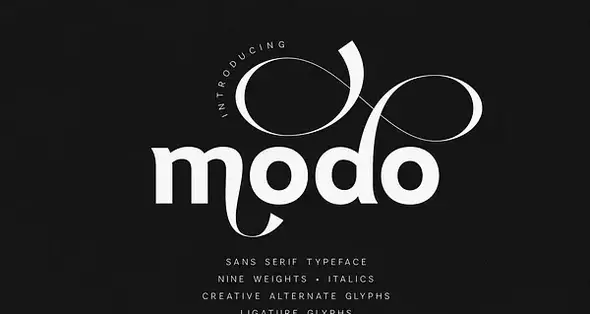
• Modo – Modern Sans Serif Typeface
Modo  فونت سنس سریف مدرن همراه با گلیف‌های جایگزین (Alternates)، لیگچر ها (Ligatures) و پشتیبانی چند زبانه. Modo یک فونت سنس سریف (sans serif) امروزی است که برای ایجاد تعادل میان مینیمالیسم تمیز و ذوق خلاقانه بیانی طراحی شده است. Modo با داشتن 9 وزن (weight) به همراه ایتالیک‌های متناظر، به‌طور یکپارچه از خطوط نازک ظریف تا عبارات بولد (bold) قدرتمند سازگار می‌شود. گلیف‌های جایگزین خلاقانه و لیگچر های شیک آن به (فونت) شخصیت می‌بخشند و آن را برای برندسازی، چیدمان‌های سرمقاله (editorial)، بسته‌بندی، لوگو و تجربیات دیجیتال عالی می‌سازند.
Modo با پشتیبانی از بیش از 85 زبان، کاربرد جهانی را تضمین می‌کند و الفبای گسترده لاتین و نمادهای تایپوگرافی ضروری را پوشش می‌دهد. چه در حال ساختن سرفصل‌های (headlines) پیچیده، متن بدنه (body text) مینیمالیستی، یا نمایشگرهای چشم‌نواز باشید، Modo یک راه‌حل تایپوگرافی همه‌کاره برای طراحان مدرن ارائه می‌دهد.
ویژگی‌های کلیدی:
• فونت سنس سریف با طراحی مدرن و همه‌کاره
• 9 وزن + ایتالیک‌های متناظر (از Thin تا Black)
• گلیف‌های جایگزین خلاقانه و گزینه‌های لیگچر
• پشتیبانی گسترده زبانی (بیش از 85 زبان)
• عالی برای برندسازی، بسته‌بندی، مجلات، پوسترها، منوها و طراحی دیجیتال
Modo – Modern Sans Serif Typeface with Alternates, Ligatures & Multilingual Support
Modo is a contemporary sans serif typeface designed to balance clean minimalism with expressive creative flair. Featuring nine weights with matching italics, Modo adapts seamlessly from elegant thin lines to powerful bold statements. Its creative alternate glyphs and stylish ligatures add personality, making it perfect for branding, editorial layouts, packaging, logos, and digital experiences.
With support for 85+ languages, Modo ensures global usability, covering extended Latin alphabets and essential typographic symbols. Whether you’re crafting sophisticated headlines, minimalist body text, or eye-catching displays, Modo offers a versatile typographic solution for modern designers.
Key Features:
- Sans serif typeface with a modern, versatile design
- 9 weights + matching italics (Thin to Black)
- Creative alternate glyphs & ligature options
- Extensive language support (85+ languages)
- Perfect for branding, packaging, magazines, posters, menus, and digital design
Bring clarity, creativity, and global reach to your next project with Modo Typeface — a modern font designed for bold ideas and timeless typography.